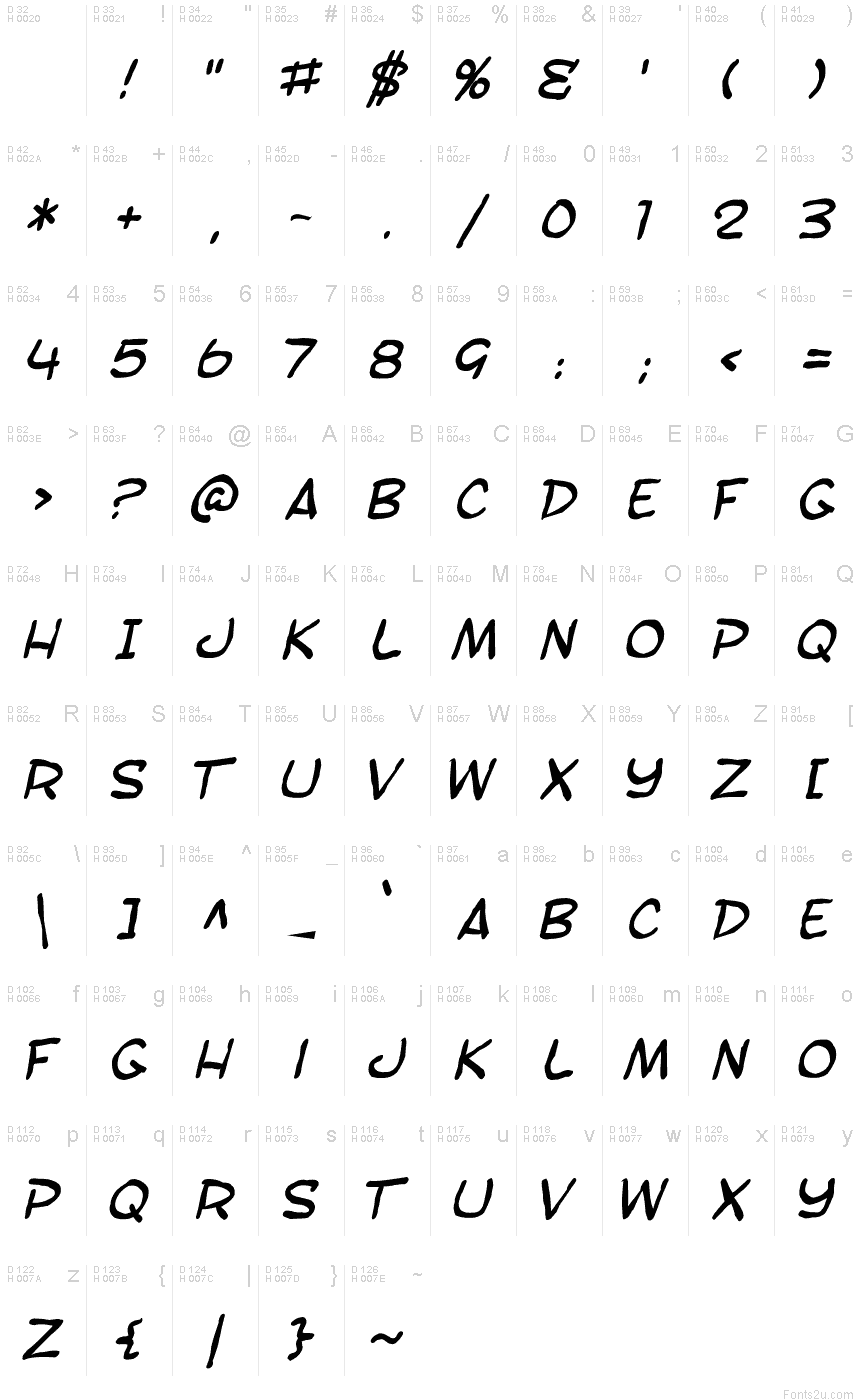
SF Toontime Blotch Italic
SF Toontime Blotch Italic od ShyFoundry to bezpłatny, komiksowy krój pisma ekranowego o luźnym, malarskim charakterze. Wielkie litery są pochylone, mają grube, zaokrąglone pociągnięcia i lekko poszarpane krawędzie, co nadaje alfabetowi żartobliwą, sobotnio-poranną dynamikę, zamiast sterylnego, kreskówkowego wyglądu.
Świetnie sprawdzi się na okładkach komiksów, ulotkach na przyjęcia dla dzieci, w zabawnych opakowaniach, planszach tytułowych i krótkich nagłówkach plakatów, gdzie potrzebny jest darmowy font z żywą, odręczną energią. Ponieważ litery są szerokie, skoczne i nieco chaotyczne, pasują również do monogramów i dużych tytułów, które mają wyglądać na improwizowane, a nie starannie zaprojektowane.
ShyFoundry
Derek Vogelpohl